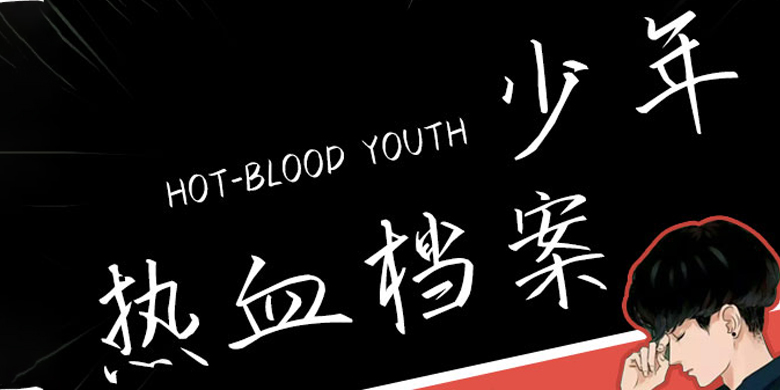
方正手迹-少年热血档案
字体品牌: 方正手迹 设计师: 刘殿儒 字体分类: 常规书写·硬笔 字体属性: 精品字 字符集: 大陆简体(GB2312-80) 发布时间: 2020
少年热血档案是一款风格鲜明的手写体,笔画锐利出笔锋,转折略微坚硬,整体字体有一种自带的风骨感。适用于文艺类的书刊、品牌广告和产品包装设计,以及社交网络的个性化用字。